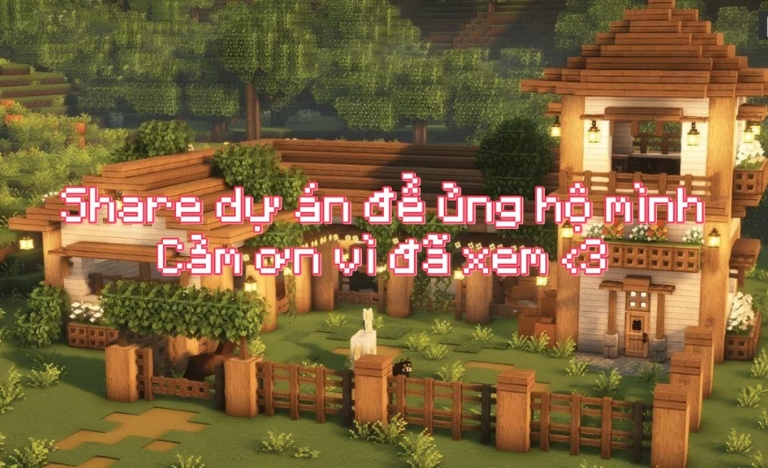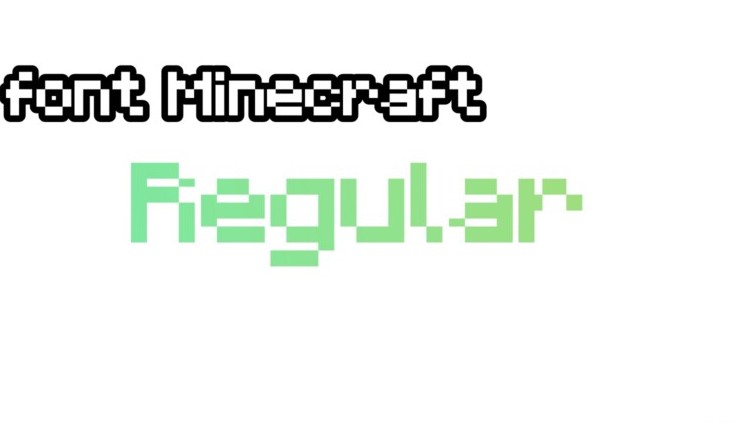
Minecraft không chỉ là một trò chơi xây dựng huyền thoại mà còn tạo ra một ngôn ngữ thiết kế đặc trưng dựa trên những khối vuông (pixel). Việc sử dụng font Minecraft Việt hóa mang lại vẻ ngoài vui nhộn, sáng tạo và đậm chất công nghệ cho các bản thiết kế.
Đặc điểm thẩm mỹ của dòng font Minecraft Việt hóa
Sức hút của font chữ Minecraft nằm ở cấu trúc dạng bitmap, nơi mỗi ký tự được cấu thành từ các ô vuông nhỏ xếp chồng lên nhau. Thiết kế này tạo nên sự đồng nhất hoàn hảo với triết lý xây dựng module, gợi liên tưởng đến những khối gạch lắp ghép trong kiến trúc hiện đại. Phiên bản font Minecraft Việt hóa đã được tinh chỉnh hệ thống dấu tiếng Việt theo đúng tỉ lệ pixel, giúp các từ ngữ giữ được vẻ vuông vức, tinh gọn và không bị lỗi hiển thị khi trình bày các nội dung sáng tạo.
Bên cạnh yếu tố hình khối, bộ phông chữ này còn truyền tải năng lượng của sự khám phá và tư duy hình học. Những đường nét dứt khoát, không có đường cong giúp văn bản trở nên tách bạch và cực kỳ nổi bật trên các nền màu đơn sắc. Đây là lựa chọn phù hợp để tạo ra điểm nhấn thị giác mạnh mẽ, giúp không gian thiết kế thoát khỏi những khuôn mẫu truyền thống và mang lại trải nghiệm thú vị cho người xem.
| Phân loại phong cách | Pixel Font / Gaming / Bitmap |
| Khả năng hiển thị | Rõ nét ở các kích thước pixel tương ứng |
| Mục đích phù hợp | Bảng hiệu khu vui chơi, Decor phòng game, Poster |
Tư vấn trình bày: Do đặc tính pixel, font chữ Minecraft Việt hóa đạt hiệu quả thẩm mỹ cao nhất khi được đặt trên các nền màu tương phản mạnh (như xanh lá, nâu đất hoặc đen). Bạn nên tránh sử dụng các hiệu ứng làm mờ nhòe cạnh chữ để giữ nguyên vẻ góc cạnh đặc trưng của phông chữ này.
03 Ứng dụng font chữ Minecraft vào thực tế trang trí
Nhờ diện mạo giàu tính gợi hình và phong cách trẻ trung, bộ phông chữ này mang lại giá trị cao trong khâu trang trí các công trình xây dựng lắp ghép:
- Hệ thống biển hiệu cho khu vui chơi trẻ em: Những nét chữ pixel rất ăn ý khi xuất hiện trên chất liệu gỗ hoặc nhựa màu sắc tại các khu homestay nghỉ dưỡng. Font chữ này giúp không gian trở nên thân thiện và kích thích sự sáng tạo của các bạn nhỏ.
- Trang trí phòng Game và Văn phòng sáng tạo: Sử dụng font Minecraft để cắt chữ nổi hoặc in decal tường tại các khu vực giải trí trong văn phòng container giúp tạo ra một môi trường làm việc năng động, mang hơi thở của thời đại kỹ thuật số.
- Bảng chỉ dẫn phong cách Retro: Bạn có thể dùng font này để làm biển tên phòng hoặc số nhà cho các công trình lắp ghép hiện đại, tạo nên một dấu ấn cá nhân đầy cá tính và khác biệt so với các phong cách truyền thống.
03 Lưu ý để bố cục font Minecraft Việt hóa không bị nhòe nét
Để khai thác hiệu quả vẻ đẹp của dòng font đặc thù này mà không làm giảm tính chuyên nghiệp của bản thiết kế, người dùng nên lưu tâm một số lưu ý sau:
- Lựa chọn kích thước phù hợp: Font pixel hoạt động hiệu quả ở các kích thước là bội số của kích thước gốc (ví dụ 16px, 32px, 48px). Việc tăng giảm kích thước không theo tỉ lệ có thể khiến các ô vuông bị biến dạng và gây mỏi mắt cho người đọc.
- Hạn chế dùng cho văn bản dài: Chỉ nên sử dụng font Minecraft cho tiêu đề, slogan hoặc các câu chỉ dẫn ngắn. Sử dụng cho đoạn nội dung dài sẽ gây khó khăn trong việc nhận diện mặt chữ và làm mất đi trọng tâm thẩm mỹ.
- Phối hợp cùng font hiện đại: Để tổng thể bản vẽ trông chuyên nghiệp, hãy phối font Minecraft (cho điểm nhấn) cùng các font không chân (Sans-serif) tối giản cho phần nội dung thuyết minh chi tiết.